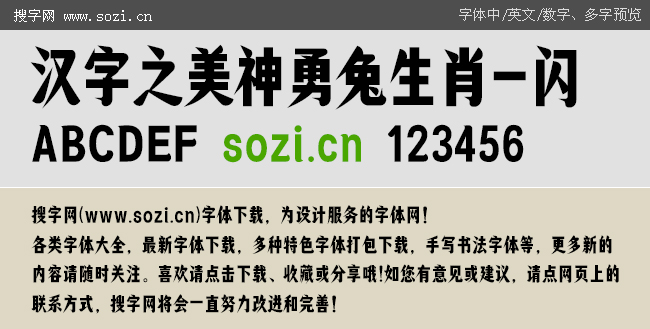
汉字之美神勇兔生肖-闪
搜字网给大家提供一款汉字之美神勇兔生肖-闪中文字体下载,汉字之美神勇兔生肖体融合宋体、黑体元素进行笔画创新,字体风格鲜明、犀利霸气,字形修长清俊,撇画凌厉,以跨时代的创新融合,探索字形的无穷变化。此字体支持在生肖主题相关设计中免费商用;支持2023年后的每年春节期间(农历正月初一—正月十五)全场景(除游戏宣传、软件内嵌、LOGO以及数字出版物)免费商用;支持兔年全年(2023年1月14日—2024年2月10日) 全场景(除游戏宣传、软件内嵌、LOGO以及数字出版物)免费商用。